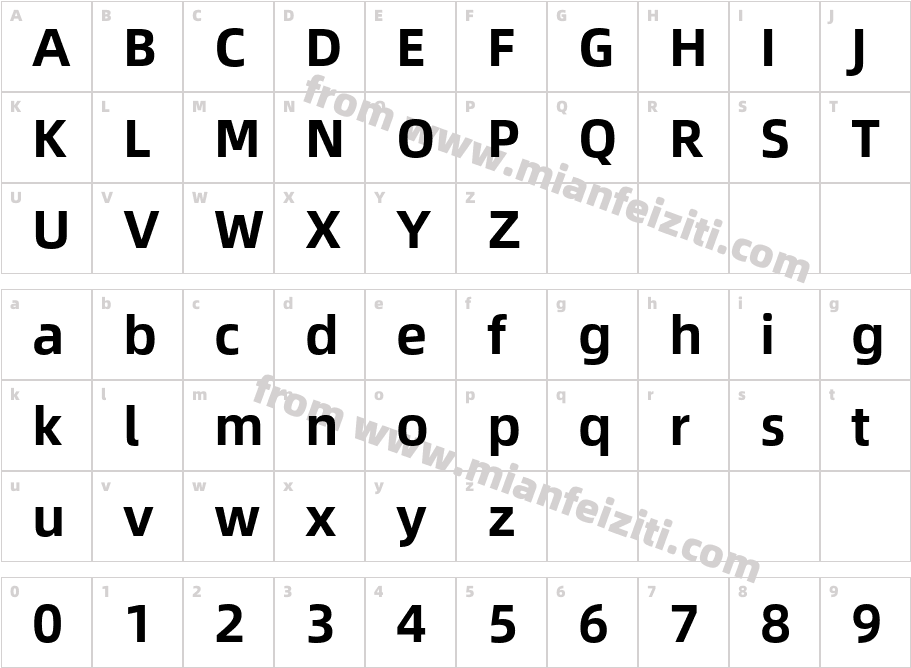
Alibaba Sans SEA Bold
字体名称: Alibaba Sans SEA Bold
Postscript名称: AlibabaSansSEA-Bold
字体品牌: 阿里巴巴
本款“Alibaba Sans SEA Bold”是一款书写很新颖的字体,字体大方,适合各种设计作品使用!欢迎下载!